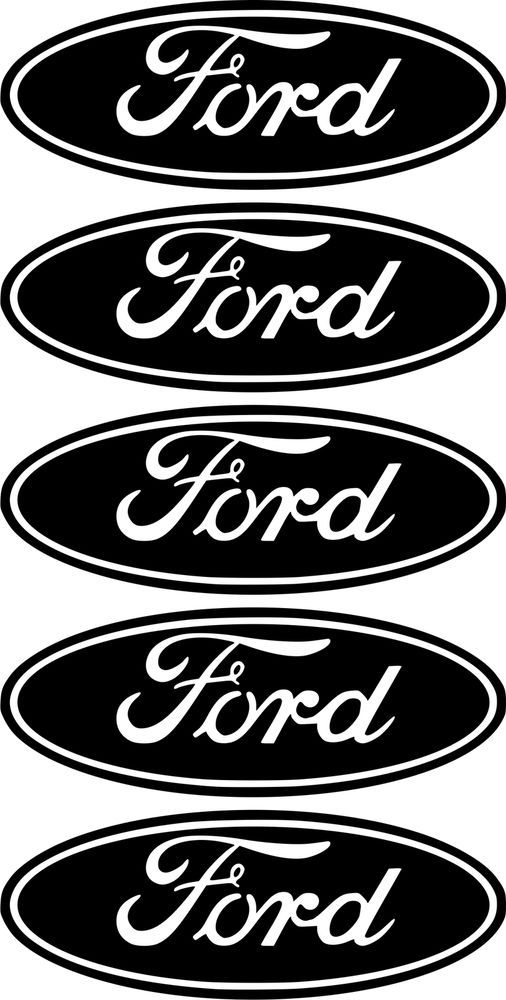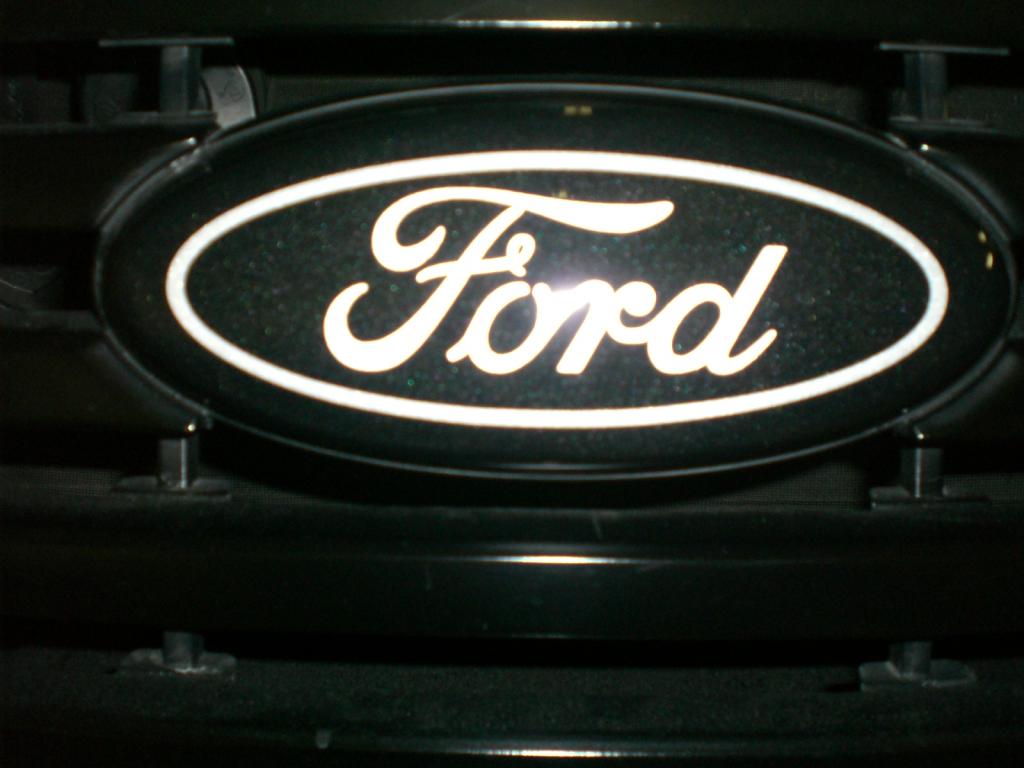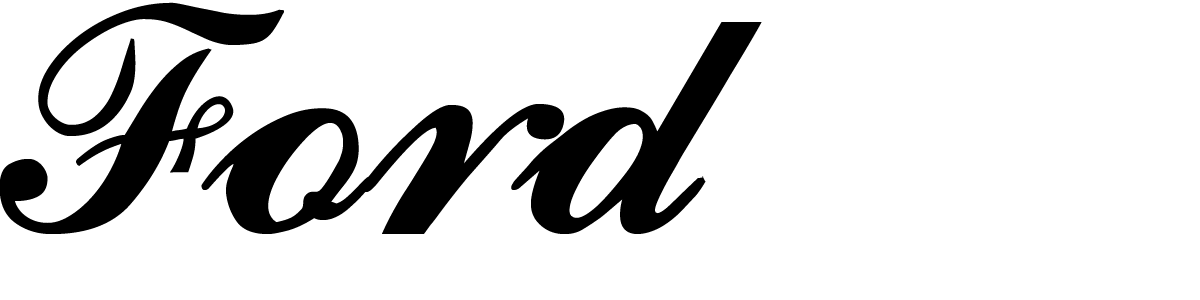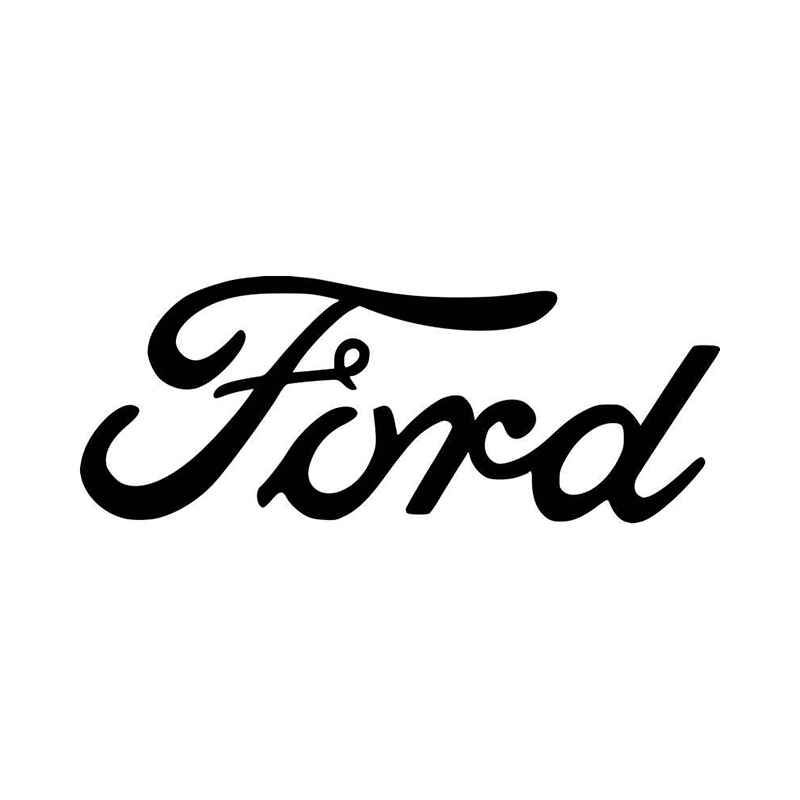
Логотип Форд: история, шрифт | Статьи о дизайне
В 1903 году мир изменился навсегда, когда легендарный Генри Форд основал собственную автомобильную компанию в Дирборне, штат Мичиган. Сегодня у бренда более 100 производственных предприятий в более чем 30 странах, каждая модель украшена культовым синим овалом.
Автомобили Форд известны во всем мире как достаточно простые и надежные. Что касается логотипа, то благодаря своей неизменности с 1927 года он стал одним из самых узнаваемых в мире. Итак, давайте подробнее рассмотрим историю логотипа Форд.
История создания Форд
В 1903 году в пригороде Детройта Генри Форд основал компанию по производству автомобилей Форд. Несмотря на сложные начинания и некоторые неудачи, ему удалось произвести революцию в мире транспорта, представив в 1908 году модель T.
Компания Форд выделялась тем, что сделала ставку на новый способ работы, называемый поточно-массовым производством, который также называют «фордизмом». Этот способ снижает затраты на строительство и резко увеличивает производство. В результате автомобили Форд стали более доступными — даже сотрудники компании могли себе позволить иметь собственный автомобиль Форд.
Генри Форд
Успех Форда быстро стал глобальным, даже в СССР. Компания также занималась производством грузовиков, тракторов и даже самолетов. Форд купил несколько конкурентов или стал крупным акционером других производителей автомобилей, включая Mazda, Aston Martin и Land Rover; но с годами американская компания сократила свои активы и продала некоторые из этих брендов, чтобы сосредоточиться на собственных продуктах. На сегодняшний день это один из крупнейших автопроизводителей, наряду с такими гигантами как General Motors, Toyota и Volkswagen.
История логотипа Форд
Эволюция логотипа Форд
История визуальной идентичности легендарного американского автопроизводителя довольно скромна.
Один из самых известных производителей автомобилей в мире, названный в честь своего основателя Генри Форда, всегда был последовательным во всем, включая дизайн логотипа.
1903–1907
Первый логотип Форд
Самый первый логотип Ford Motor Company состоял из богато закругленного значка в рамке с листьями и изгибами. Значок был окрашен в черный цвет с белой надписью и в белой рамке. Буквы были изогнуты и расположены волнообразно, с подписью «Детройт, Мичиган» жирным шрифтом без засечек. Это была традиция для своего времени, очень элегантная и простая.
1907 — 1909
В 1907 году Форд решает сменить свой стиль на современный и строгий. Теперь эмблема имеет совершенно новый стиль и форму — ромб с закругленными плавными углами имеет жирную черную надпись «Ford» посередине и дополнительную надпись сверху и снизу.
Форма нового значка, напоминающая глаз, сделала весь логотип запоминающимся, а его цветовая палитра из металлически-серого и черного добавила ощущения профессионализма и прогрессивного подхода.
1909 — 1911
В 1909 году логотип компании представлял надпись Ford, выполненную изящным курсивным шрифтом. Сегодня он по-прежнему составляет основу всей концепции компании, только с небольшими изменениями и новой цветовой палитрой.
В надписи присутствует удлиненный хвост буквы «D», который в дальнейших версиях будет удален.
Вариант 1910-х годов был выполнен в монохромном стиле и не имел обрамления.
1911-1912
В 1911 году компания модернизирует свой логотип. Теперь назпись заключена в двойной горизонтальный овал, по периметру которого размещена надпись «The Famous Motor Cars».
1912-1917
Версия 1912 года — самая интересная. Теперь надпись Ford расположена на синем значке, стилизованном под птицу. Все детали выполнены в белом цвете на синем фоне, есть тонкий, но строгий слоган «Универсальный автомобиль». Этот дизайн оставался у компании пять лет.
1917-1927
В 1917 году Форд решает вернуться к минимализму, изменив логотип 1911 года.
Теперь подпись Генри Форда помещена внутри белого овала с тонкой рамкой. Это был простой, но очень элегантный логотип, просуществовавший десять лет.
1927 — 1957
Цветовая палитра была изменена на сине-белую в 1927 году. Немного изменена рамка. Этот логотип стал прототипом того, что мы все знаем сегодня.
1957-1961
В 1957 году Форд снова модернизирует свой значок. Это был дизайн, который просуществовал недолго, хотя и оказал влияние на будущие версии.
1961 -1976
Логотип, разработанный в 1961 году, немного изменил цвет, форму и приобрел дополнительную рамку. Этот лого использовался автопроизводителем в качестве основного в течение 15 лет.
1976 — 2003
В 1976 году Форд решает использовать трехмерную версию, сменив белый цвет на серебристый и добавив блеска поверхности значка. Синий здесь более темный и имеет градиентные оттенки.
2003 — Сегодня
Версия 2003 года похожа на версию 1961 года, но более легкая.